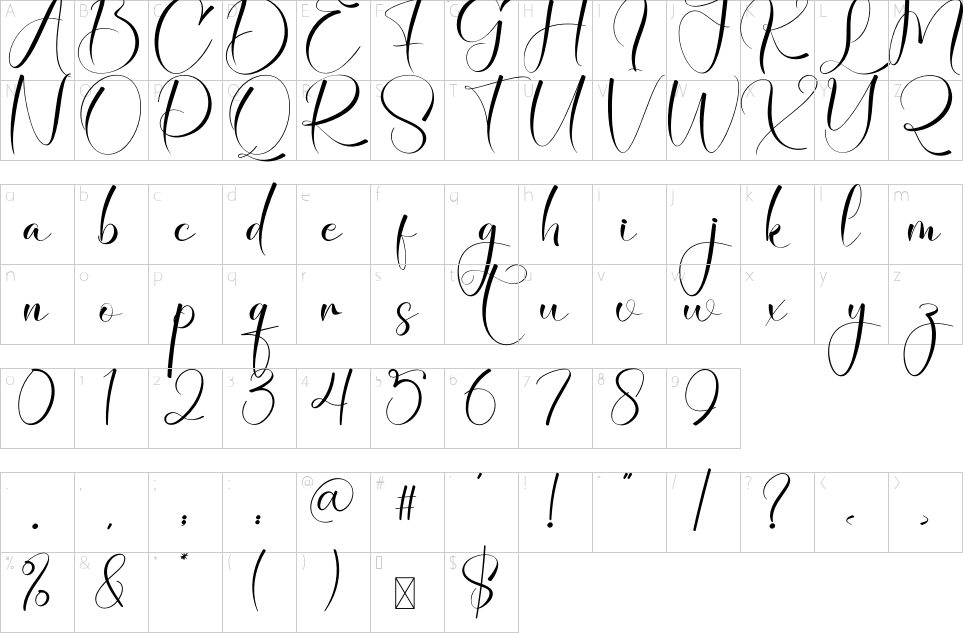
Descobrir uma nova fonte é como desfrutar uma folha de vinho, única em sua elegância e complexidade. A Samantha Flower é uma fonte que transmite essa sensação de beleza e sofisticação. Ela foi criada por uma designer anônima, mas seu design esmerado e alegre tornou-a uma opção indispensável para qualquer projeto de design gráfico. Com sua tipografia floral e delicada, Samantha Flower é uma escolha ideal para criar designs de blogs, e-books, ou qualquer outro projeto que valorize uma aparência delicada e sofisticada. E, graças à sua disponibilidade gratuita, qualquer designer pode experimentar e explorar seu potencial. Há 1.135 downloads da Samantha Flower, um número que se aprofunda no sucesso desta fonte. Seja você um designer ou um amante de design, Samantha Flower é uma fonte imperdível que certamente enriquecerá o seu trabalho.